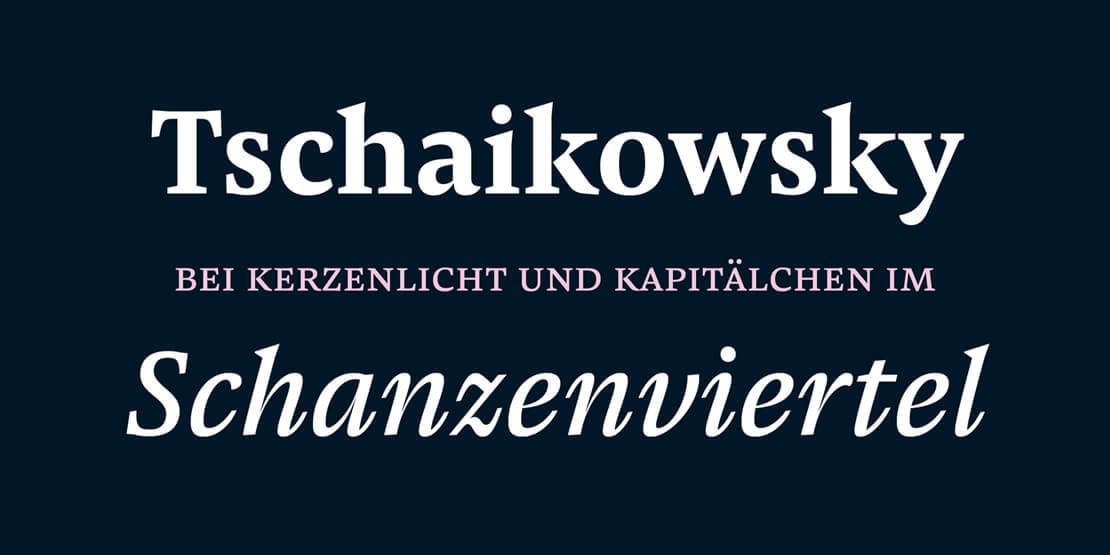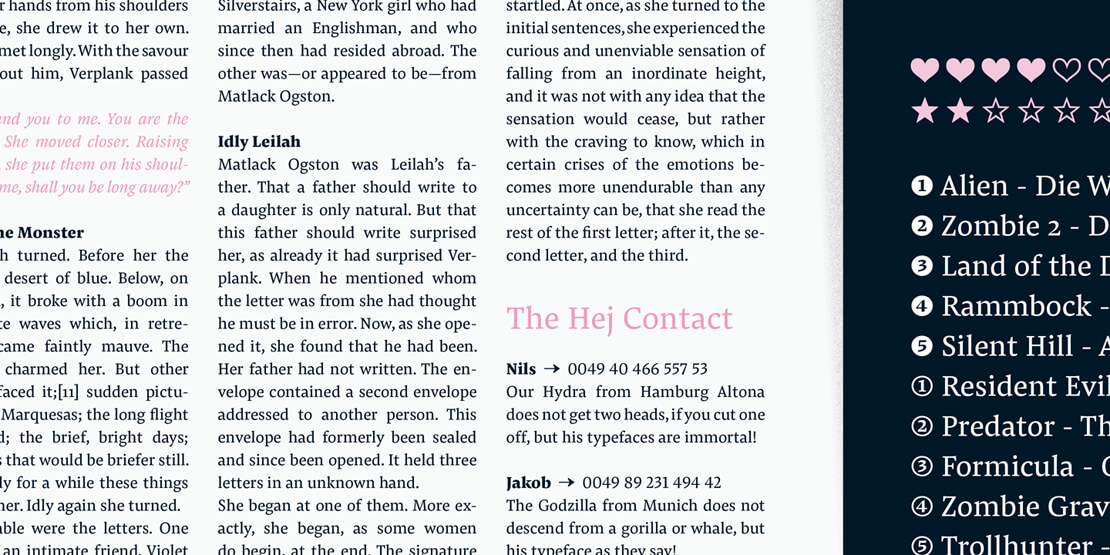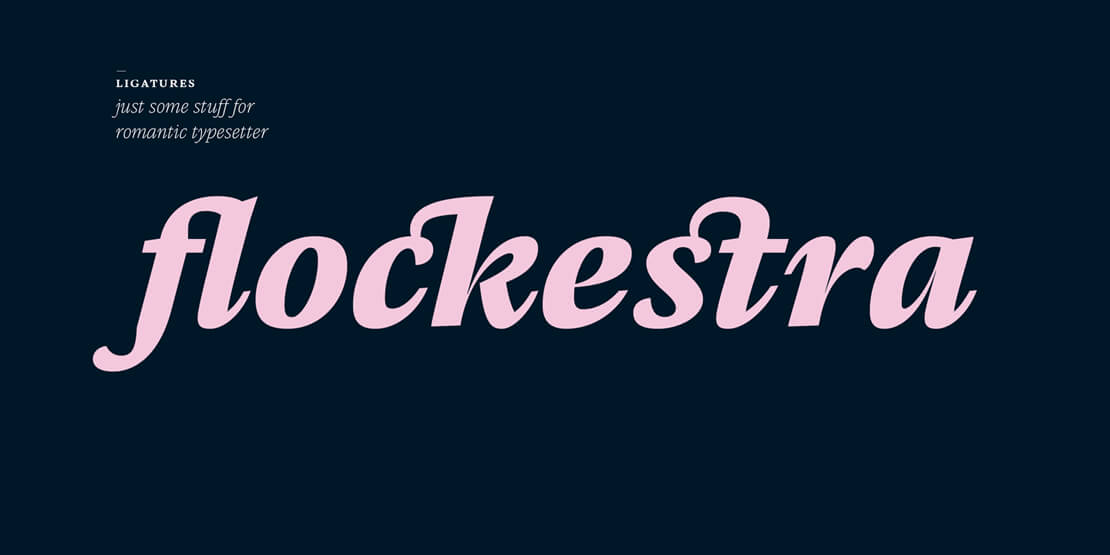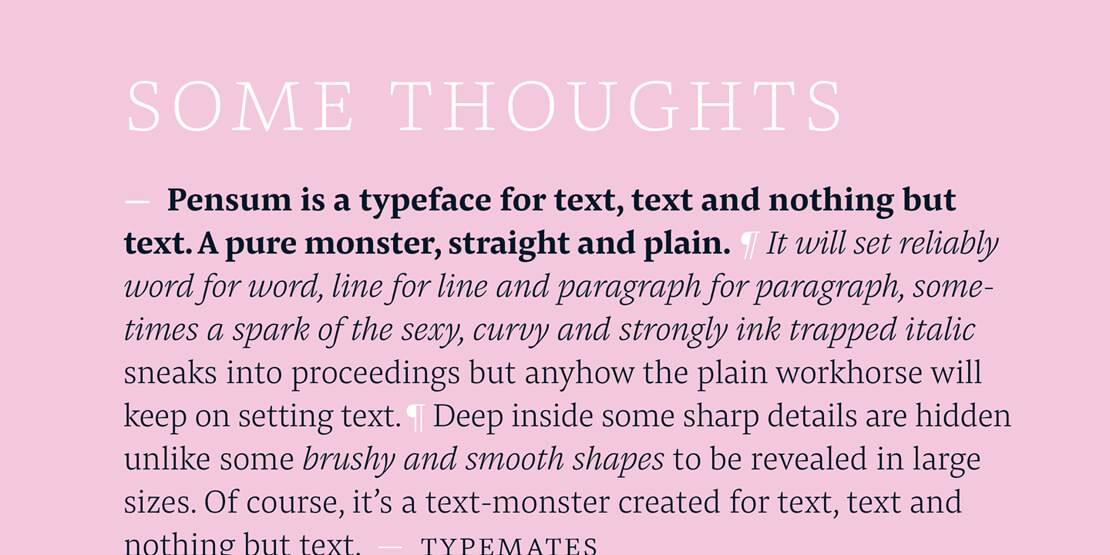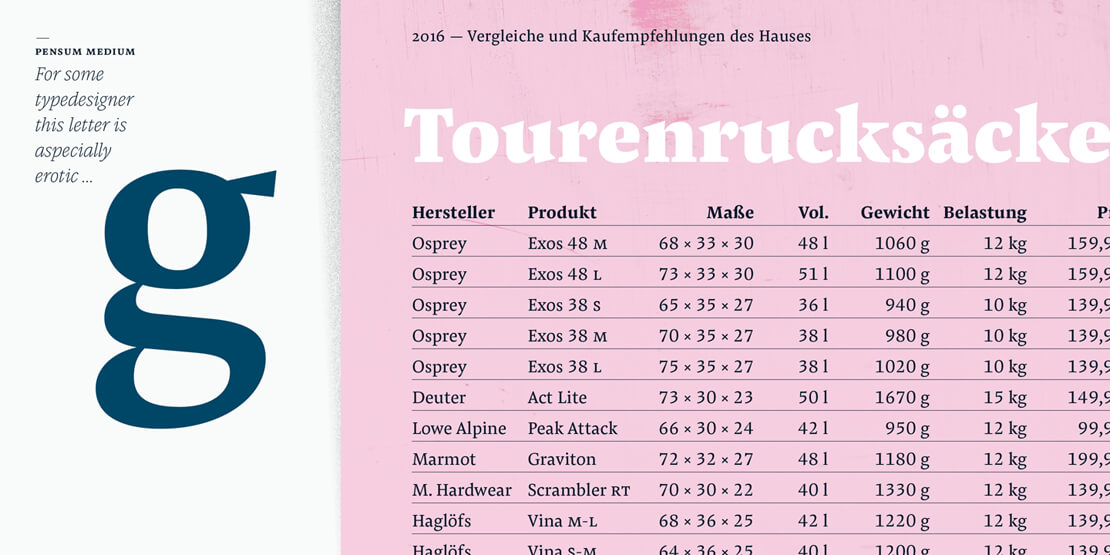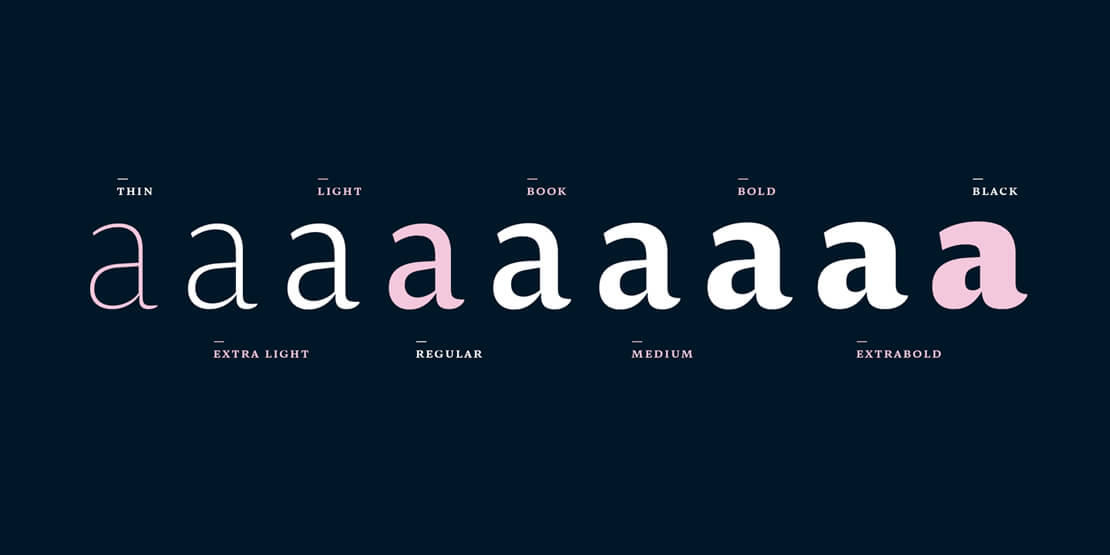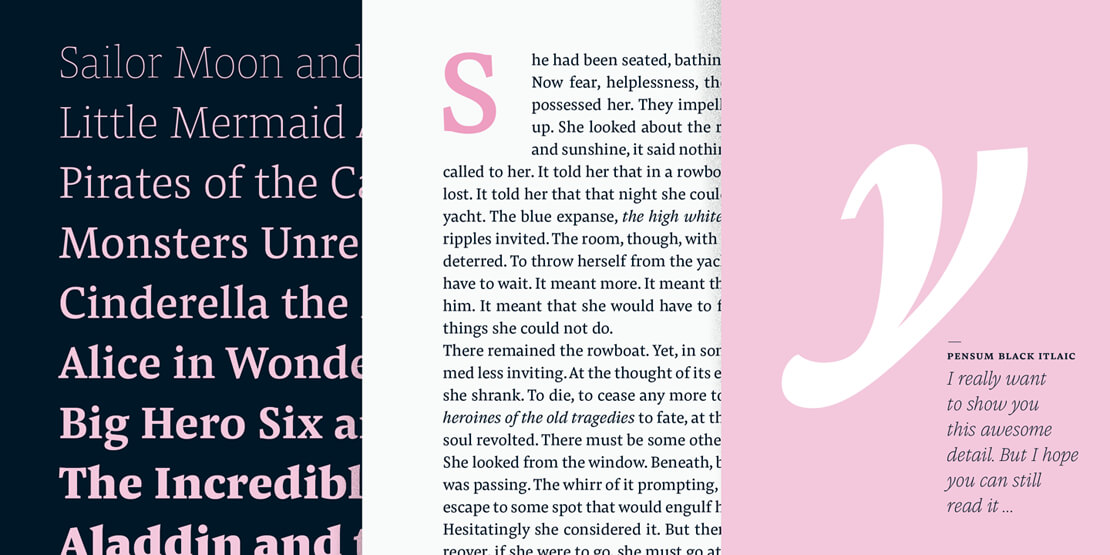
»Pensum Pro« von Nils Thomsen
Bei den TypeMates aus Hamburg ist »Pensum Pro« von Nils Thomsen erschienen: eine Breitfeder und Pinsel inspirierte Schriftfamilie mit neun Gewichten, die sich auch für lange Lesetexte eignet.
»Pensum« ist durch Formübungen mit der Breitfeder und dem Pinsel in der Klasse von Peter Verheul, während Nils Thomsens Zeit vom »Type and Media« in Den Haag 2009, entstanden. Schon damals war der Designer auf der Suche danach, ansprechende Details in Einklang mit einer simplen und schlichten Schrift zu erzielen.
Die neun Gewichte von »Pensum Pro« reichen von »Thin« bis »Black« und lassen sich unter anderem in Magazinen, Büchern und Co. verwenden. Die Schriftfamilie beinhaltet rund 1.050 Zeichen sowie OpenType-Features – von Kapitälchen für Buchliebhaber bis hin zu Satzzeichen, die sich entsprechend dem Versal- oder Kapitälchensatz anpassen.